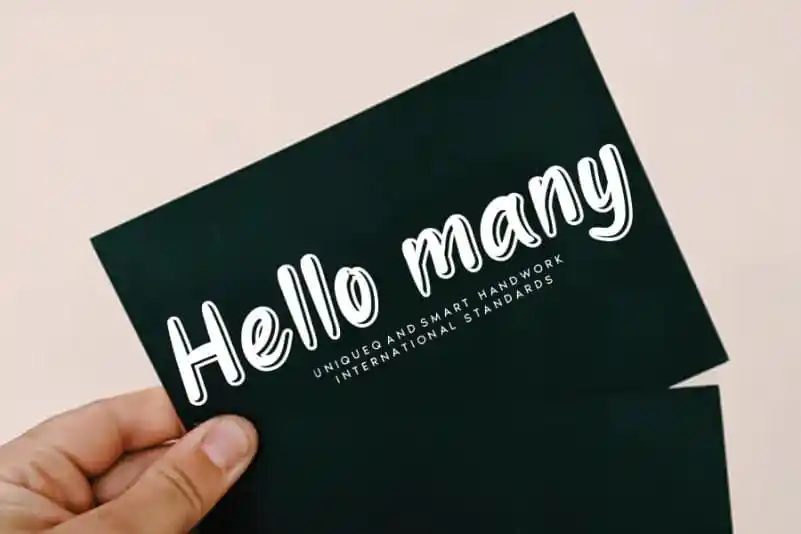
Hello many Display Font – Fonte Grátis
Hello many Display Font
O ‘Hello Many Display Font’ é uma elegante escolha para aqueles que buscam uma fonte capaz de capturar a atenção. Seu estilo fluido e versátil permite criar um amplo leque de designs, desde invitations para casamentos até arte de estação, postagens interessantes em redes sociais e muito mais. Através da sua flexibilidade, o ‘Hello Many Display Font’ proporciona uma experiência visual atraente que complementará qualquer projeto design. Como designer de fontes, estamos certos de que essa nova adição para a nossa biblioteca de fuentes irá trazer diversão e estilo para seu próximo trabalho artístico.